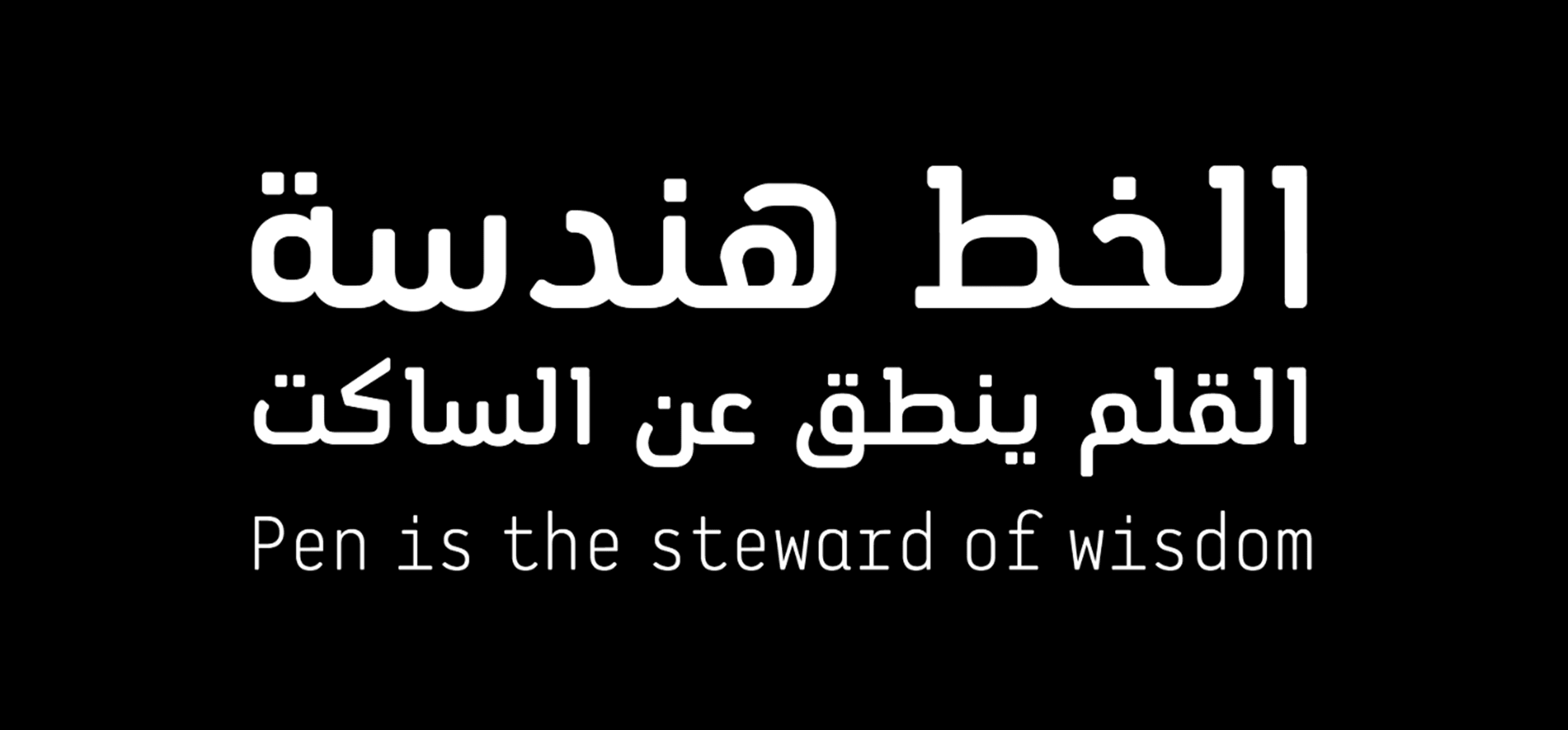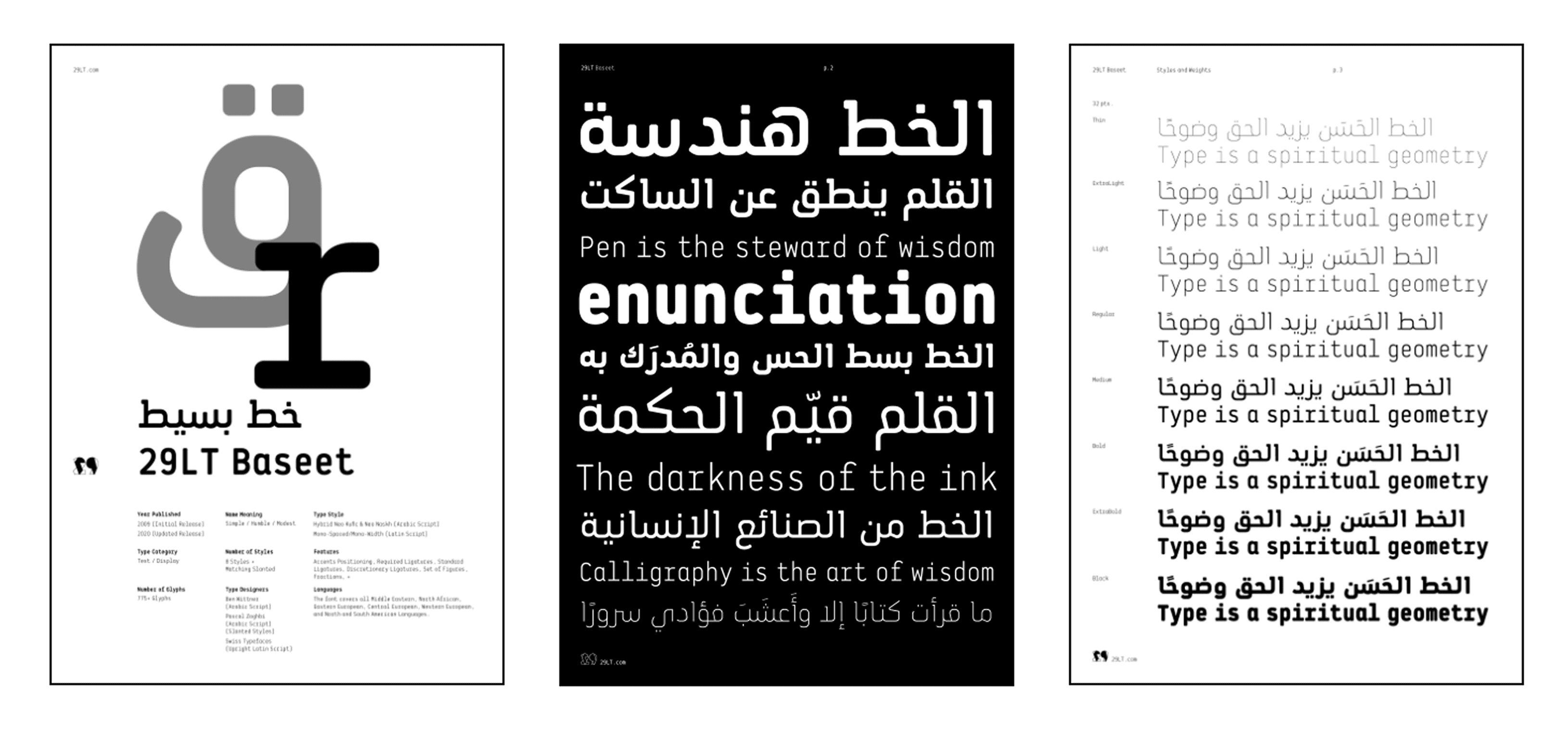
يتميّز 29LT Baseet ببنية هندسية مستقرة ووزن بصري متوازن يجمع بين القوة والود في آنٍ واحد. صُمم ليكون عمليًا وسهل القراءة، ما يجعله مناسبًا لتصميم العناوين، واجهات التطبيقات، الإعلانات، والمشاريع الطباعية الحديثة.